Trong thế giới thiết kế hiện đại, font chữ không đơn thuần là công cụ trình bày chữ viết, nó là "giai điệu thị giác" giúp truyền tải cảm xúc, phong cách và cả âm thanh ngầm trong từng thiết kế. Font chữ âm nhạc là thuật ngữ chỉ các kiểu chữ mang hơi hướng âm nhạc, có thể là sự mềm mại của acoustic, sự nổi loạn của rock, hay sự cao cấp trong opera.
Khác với font chữ truyền thống, font âm nhạc thường được thiết kế với nhịp điệu riêng, độ cong, độ dày, hay texture gợi lên cảm giác như đang lắng nghe âm nhạc. Trong thiết kế poster sự kiện, album, MV hay branding âm nhạc, việc chọn đúng font là bước quan trọng giúp thiết kế chạm đúng cảm xúc người xem.
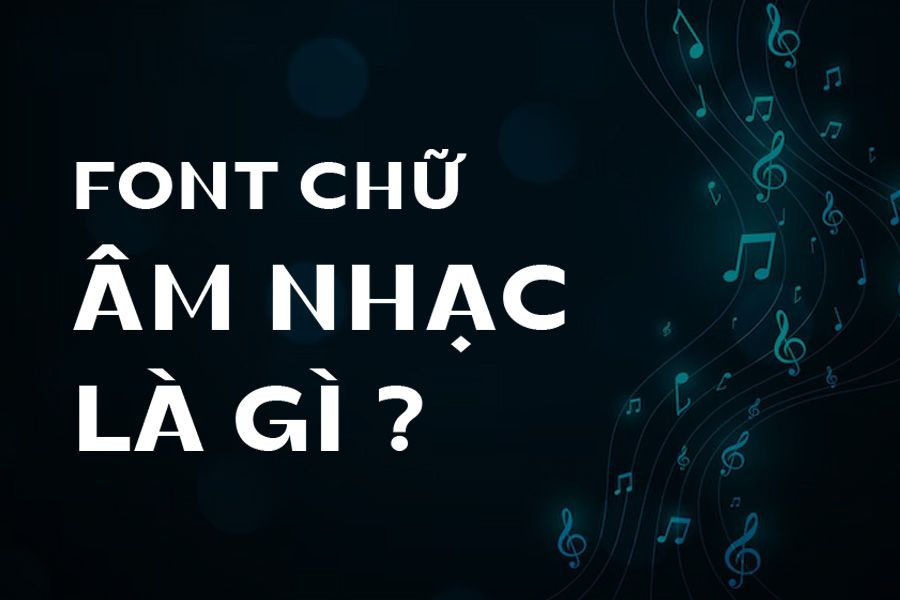
Khi lựa chọn font chữ âm nhạc Việt hóa, có 3 yếu tố bạn cần cân nhắc:
Khả năng hỗ trợ tiếng Việt đầy đủ: Font cần hiển thị chính xác dấu câu, không lỗi tiếng Việt.
Phong cách âm nhạc phù hợp: Chill, ballad, pop, acoustic, EDM hay giao hưởng – mỗi phong cách đòi hỏi cảm xúc và kiểu chữ khác nhau.
Ứng dụng thực tế: Font vừa đẹp vừa phải dễ đọc trên poster, banner, social media hoặc bìa album.
TH Cameo Sans là kiểu sans-serif tròn đều, thân thiện, mang lại cảm giác thư giãn và tinh tế, rất lý tưởng cho các thiết kế mang âm hưởng acoustic hoặc môi trường spa yên bình. Font gốc được thiết kế bởi Daletto Studio, sau đó được Việt hóa hoàn chỉnh bởi Phạm Sơn - S99.VN với đầy đủ dấu tiếng Việt, phù hợp tiêu đề lớn và branding ngành thẩm mỹ.
Lấy cảm hứng từ các thương hiệu cao cấp và dòng nhạc chill nhẹ nhàng, TH Luxury 8 có phong cách sans-serif thanh mảnh, tối giản và không gian thoáng. Font gốc bởi Craft Supply Co., Việt hóa bởi Phạm Sơn - S99.VN, rất phù hợp trong poster Lo-fi, podcast hoặc bìa album có chiều sâu cảm xúc.
TH Galvitra là display font dạng sans-serif với đường nét hình học sắc sảo, mang đến cảm giác sôi động, thích hợp cho các thiết kế về nhạc điện tử, EDM hoặc sân khấu biểu diễn. Font được thiết kế bởi Fontastica x Nasir Udin, và được Việt hóa bởi Phạm Sơn - S99.VN, hỗ trợ thiết kế poster lớn và headline thương hiệu âm nhạc hiện đại.
Pinland là font viết tay nhẹ nhàng, mang nét mộc mạc và tự do – rất thích hợp với dòng nhạc indie, acoustic hay thiết kế lyric poster. Font gốc từ Timur Type, được Việt hóa bởi Phạm Sơn - S99.VN. Các đường nét mềm mại giúp thể hiện sự gần gũi và cá tính nhẹ nhàng trong thiết kế nghệ thuật.
Ervha mang hình thức gọn gàng, hiện đại của một sans-serif đơn giản nhưng đầy hiệu quả, phù hợp các dự án pop, ballad hoặc social media. Font gốc của Graphicxell Studio, Việt hóa bởi Phạm Sơn - S99.VN, giữ nguyên form chữ cân đối, dễ đọc, và tinh tế trong tiêu đề hoặc caption bài nhạc.
The Mantra Key gợi liên tưởng đến những poster synthwave thập niên 80 pha lẫn nét đương đại. Font có sức hút thị giác mạnh với kiểu dáng retro và spacing rộng. Thiết kế gốc bởi VP Creativeshop, Việt hóa bởi Phạm Sơn - S99.VN, rất hợp poster comeback, K-pop hoặc thiết kế âm nhạc theo xu hướng hoài cổ.
Mang tinh thần thanh lịch và cổ điển, TH Luxury 3 sử dụng trong các thiết kế cần sự đẳng cấp như sân khấu giao hưởng, opera hoặc branding phòng trà. Font được phát triển bởi Balibilly Design, Việt hóa kỹ lưỡng bởi Phạm Sơn - S99.VN, cân đối tốt giữa yếu tố nghệ thuật và sang trọng.
Honest Proud là sans-serif tôn trọng sự tối giản nhưng không mất đi tính uy nghi. Với các nét gãy gọn và chiều cao đồng đều, font cực kỳ phù hợp để xây dựng hệ thống nhận diện thương hiệu hoặc banner sự kiện âm nhạc. Font gốc bởi Nirmana Visual, Việt hóa bởi Phạm Sơn - S99.VN.
TH Grotley mang hình thức hiện đại của các font geometry sans-serif cao cấp, rất phổ biến trong branding ngành công nghiệp giải trí, thời trang và K-pop. Font gốc do Craft Supply Co. phát hành, được Việt hóa đầy đủ bởi Phạm Sơn - S99.VN, giúp bạn dễ dàng tạo nên thiết kế trẻ trung, nổi bật.
Lấy cảm hứng trực tiếp từ phong cách của nhóm nhạc BlackPink, font Born Pink có thiết kế mạnh mẽ nhưng vẫn nữ tính, phù hợp cho các chiến dịch âm nhạc thời thượng hoặc sản phẩm truyền thông hướng đến phái nữ. Font thiết kế bởi Zealab Fonts Division, Việt hóa bởi Phạm Sơn - S99.VN – mang hơi hướng nữ quyền hiện đại.
Font chữ không chỉ truyền tải thông tin, mà còn truyền cảm – đặc biệt trong âm nhạc. Từ vibe thư giãn, sôi động, cho đến cá tính, mỗi font trong bài viết đều mang màu sắc riêng, giúp bạn dễ dàng chọn lựa cho dự án âm nhạc cá nhân hoặc chuyên nghiệp.